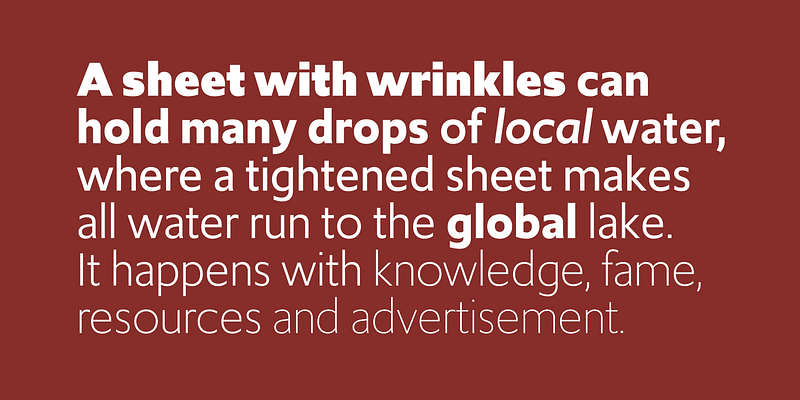
Orientada a flujos de trabajo automatizados, la amplia y polivalente actualización es el primer lanzamiento tradicional de Petr van Blokland en años. Los generosos conjuntos de caracteres y características de esta Sans Serif de bajo contraste la convierten en una bendición para la tipografía compleja. TYPETR, 2018.
Nacido en Gouda, Países Bajos, en 1956, Petr van Blokland se graduó cum laude del programa de artes gráficas de la Real Academia de Bellas Artes (KABK) de La Haya en 1980.
Con su socia Claudia Mens, Van Blokland trabajó durante más de treinta y cinco años como diseñador en el estudio que cofundaron. Su producción abarcó desde bocetos y maquetas hasta programación en varios lenguajes. Se especializó en diseño sistemático: identidades corporativas, sistemas de formularios, publicaciones en línea y herramientas para el diseño tipográfico.
Después de décadas de publicar a través de Font Bureau, Petr van Blokland cofundó Type Network, donde lanza exclusivamente nuevos tipos de letra bajo la etiqueta TYPETR. Tiene pensado publicar nuevas familias regularmente y también escribirá publicaciones educativas ocasionales sobre diseño gráfico, tipografía en general y cómo usar la tipografía en particular.